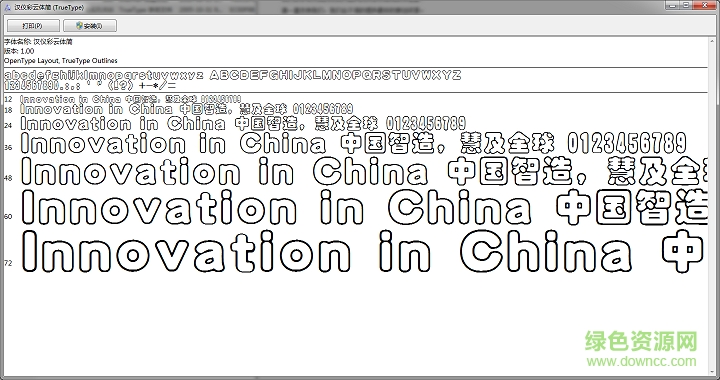
hyl1gj
hyl1gj字體(漢儀彩云體簡(jiǎn))是一款新穎獨(dú)特的空心字體,該字體筆畫清晰,飽滿圓潤(rùn),具有很好的裝飾作用,廣告、雜志、海報(bào)、網(wǎng)頁都可以使用這款個(gè)性字體,喜歡的朋友快來下載吧!
空心字介紹
hyl1gj字體特點(diǎn)
該字體是專門針對(duì)設(shè)計(jì)而開發(fā)的一款中文簡(jiǎn)體漢字,字體呈空心狀,端正大方,筆畫的中間留出空白,似一朵朵浮云,整體效果非常出眾,可以應(yīng)用于廣告設(shè)計(jì)、名片設(shè)計(jì)、包裝印刷、產(chǎn)品設(shè)計(jì)等應(yīng)用!